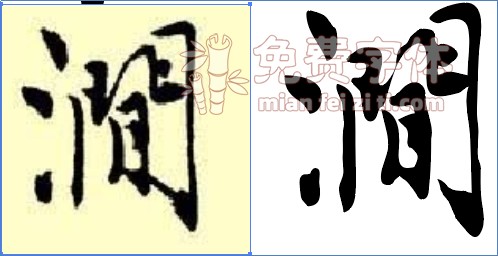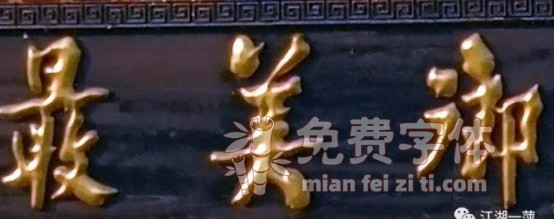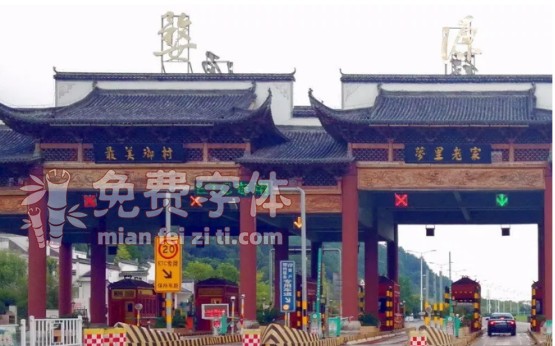
唐伯虎天下第一行书创作记录字体资讯
我们在创作这一字体的过程中,既尊重原帖,又试图修正传世碑帖的一些缺陷。
这种对缺陷的把握,往往决定字库生产厂商的水平,比如在婺源的门碑中,就有这样案例:
上图:最、乡,二字是明显的错字,但却存在时下诸多字库中。
逐浪人认为作为标准字库,在保持和尊重书法家艺术风貌的基础上,应该维护字体的基本要义和规范。
如下面帖中的“涧”字
我们对其进行了优化,使之符合汉字布局,既尊重原帖,又不拘泥原帖,入帖出帖自有章程。